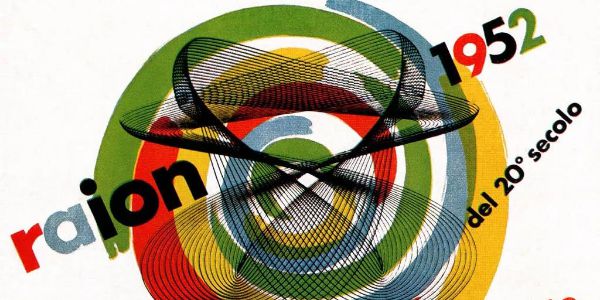
他的设计疯起来真是六亲不认一马克斯・赫伯
Max Huber(马克斯·赫伯)是20世纪欧洲广告界的领军人物,他丰富而多面向的个性,使他的作品也带有灵动且无法预料的迷人风格。
赫伯是最早在意大利的广告海报中尝试使用照相技术的人之一。他将色彩的套印与照片结合使用,制造了强烈的实验意味。然而这种先锋的版面效果却从不会落入杂乱和无序。从上面的作品中,我们能看到赫伯总是能用极度严谨的设计功力将版面控制在一个微妙的平衡点,甚至还带点迷幻。这与他所接受的瑞士设计教育密不可分。他的设计就像他最痴迷的爵士乐一样,灵动随意,极富变化性,却又有着精准的节奏感。下面这些作品运用的都是类似的手法,但却各有各的魔幻。你感受一下。
米兰工业大学室内建筑与设计史教授,意大利知名策展人 Giampiero Bosoni 对赫伯有着极高的评价。
Giampiero Bosoni
“他是多种美妙事物的混合体,他有着非凡的艺术天赋和完美的设计功力,他像个孩子一样活泼和坦率,同时又具备瑞士学派的高度严谨,他热爱创新,拥有永不枯竭的好奇心,随时能够抓住不可预测的新想法,并能以一流的专业水准精确地呈现出来。”
设计师简介
Max Huber(马克斯·赫伯)1919年出生于瑞士,当时第一次世界大战刚过,整个欧洲元气大伤,选择在这个时间点出生在欧洲的他,注定了设计生涯与战争有着密不可分的关系。赫伯从很小的时候起,就表现出了极强的视觉艺术天赋,1935年,17岁的赫伯高中毕业后进入了瑞士苏黎世工艺美术学院,但由于家人无力承担他的学费,赫伯入学不到一年就开始了半工半读的状态。然而没钱根本不算什么,因为接下来你将目睹他一边逃难一边做设计。你再难你也没他难。
赫伯在学校结识了许多优秀的艺术家,其中对他影响最大的是他的图形和摄影老师Alfred Willimann,他让赫伯接触到了俄国构成主义和德国的包豪斯,引导赫伯走向了一种严谨和理性的设计风格,也就是我们今天说的“瑞士风格”,也叫“国际印刷风格”。说到瑞士风格,我们脑中多多少少都会浮现出一些性冷淡的设计,它们强调清晰,可读性和客观性。风格的标志是不对称的布局,使用网格系统,无衬线字体以及左侧对齐右侧参差的文本编排方式。
魏玛时期的包豪斯学院
国际印刷风格是德国包豪斯的探索成果在瑞士的延续,由于包豪斯在德国被纳粹关停,一部分遭到打压的艺术家被迫流亡到了瑞士。他们与许多年轻的瑞士同事一起开创了国际印刷风格,奠定了瑞士平面设计的基础。
然而欢乐的时光总是短暂的,一转眼就到了分手的时刻。1939年二战爆发,虽然作为中立国的瑞士奇迹般地没有被战争波及,但身处战乱年代的瑞士,全国上下随时做好了抵抗的准备。为了躲避征兵,赫伯决定先走一步,1940年12月他来到意大利米兰发展,这使他成为众多进军米兰的瑞士设计师中的第一人。21岁的赫伯初到米兰,就决定到博格瑞工作室(STUDIO BOGGERI)应聘。
STUDIO BOGGERI,意大利最重要的设计工作室之一
问题是他几乎说不了几句意大利语,即便如此,在创始人Antonio Boggeri看到了赫伯留下的名片之后,立即决定雇用这位年轻的设计师。因为Boggeri注意到名片上整齐的小写字,看起来是印刷的,但其实是手写的。字母的间距微小却精确,足见赫伯当时扎实的设计功底。
Max Huber手写名片,1951
我没有找到当时他应聘用的那张名片,但这张手写名片是赫伯加入博格瑞后于1951年制作的,尺寸是60mm*135mm,上面的手写文字大小相当于Bodoni的10pt。这就是别人的手。
赫伯把米兰,尤其是博格瑞工作室,看作是一个插图、绘画、摄影和印刷都可以融合在一起熔炉。在博格瑞,他又能与设计界的领军人物、知识分子和前卫艺术家们在一起愉快地玩耍了。
赫伯在博格瑞从事的工作包括设计海报、画册、展会、橱窗、文件夹、文具、广告、商标——事实上,他所开展的工作,其他国家直至20多年后才出现。
不过赫伯初到米兰的设计工作仅维持了18个月就被迫终止了,1942年由于战争原因,赫伯再次决定跑路,返回瑞士躲避战乱,一年之后,英军登陆西西里岛,战火烧至意大利本土。
年轻的赫伯与他的设计师朋友们
回到瑞士后赫伯也没闲着,他在苏黎世加入了瑞士艺术家联盟协会,该协会的领导人也叫马克斯——马克斯·比尔(Max Bill)。这位马克斯早在1936年的米兰三年展中,就通过其展馆设计得到了设计界的肯定。在战争期间,赫伯与比尔合作从事展览设计工作,受到其很大的影响。
MAX BILL(建筑师,工业设计师,平面设计师,画家)
1970年
1946年,二战结束后的第一时间,赫伯又搬回了米兰,他认为在战后,设计有恢复人类价值的能力。这种人性化的设计理念在20世纪50年代在整个欧洲流行起来。当时他被意大利最大的出版商Einaudi任命为创意总监。
La formazione della Cina Moderna
书封,Einaudi
作为该出版物的创意总监,他接触了大量战后的意大利知识分子。随后的岁月被认为是他一生中最富有成效的时期。他在20世纪40年代后期制作了一系列史诗级且富有影响力的设计。作为一名热衷爵士乐的粉丝,他设计了许多令人惊叹的唱片封面,音乐杂志和爵士音乐节,都是20世纪平面设计史上非常经典的设计案例。
Max Huber 与“爵士乐之父”Louis Armstrong
上图是赫伯与自己的偶像路易斯·阿姆斯特朗握手的画面,见到爱豆的赫伯秒变迷弟。Giampiero Bosoni 曾在瑞士策划过一场专门以爵士乐为主题的赫伯作品展,展出的大量作品中还包括许多从未出版过的作品,足见赫伯对于爵士乐的狂热。
赫伯对平面设计的贡献得到了高度赞赏,最终他于1954年获得了著名的Compasso d'oro奖(意大利工业设计界的最高荣誉,同时也是欧洲同类设计奖中的首个奖项)。此外,他于1958年作为演讲者参加了第一届印刷术国际研讨会(纽约艺术指导俱乐部)。
随着他的艺术作品在国际上受到欢迎,越来越多的国家展出了他的作品。1965年,日本设计委员会在东京松屋艺廊举办了一场展览,展示了赫伯的作品。这次展览使他与日本建立了密切的联系,他还在这里找到了日后的妻子,日本设计师河野鹰思的女儿,插画家Aoi Kono。从此全家都是搞艺术的。
Max Huber 与 Aoi Kono
晚年,赫伯开始教授设计,他的一生都在从事设计工作。直到1992年,作为一位影响了世界平面设计史的设计师,Max Huber在瑞士门德里西奥逝世,享年73岁。
m.a.x. Museo
2005年,m.a.x. Museo——一个致力于纪念 Max Huber 的博物馆——在瑞士 Chiasso 成立,用于保存他的个人档案及作品,也用于展出许多优秀的当代平面艺术家的作品,同时也是平面设计爱好者的朝圣之地。
作品解析
fotolux 销售目录〈1940〉
Fotolux是一家照片复印公司,画面中的主体Fotolux采用了镜像的手法,用将“复制”这一概念视觉化的方式来表现公司的核心业务。这是赫伯初到米兰,在Boggeri工作室的早期设计之一。其中精细的手写字体,考究的小写字母间距,透视和有限颜色的使用,都展示出赫伯在瑞士接受设计教育的特点。
葛兰素实验室的 Adexolin(阿霉素)
药学手册〈1941〉
Adexolin是一种维生素A、D制品,这本药学小册子介绍了维生素A和D的“生物学前提和治疗应用”。完全听不懂。在当时的历史背景下,米兰的许多设计师的设计作品都依赖于药品宣传。赫伯将产品名中的“AD”与维生素“A”和“D”单独涂成白色,以强调产品本身和所含维生素之间的联系。
Teweka 金属扣环广告〈1941〉
这幅广告设计采用了照相技术,照片显示金属扣环就像是刚刚从盒子里掉出来散落一地的样子,是很有现场感的一张照片。赫伯将这张照片铺满整个版面,但是版面还得有个主体,他从背景中挖出一个扣环的放大轮廓,将品牌名称和唯一的一句广告语与扣环轮廓组成一个组合,颇具视觉冲击。
Procedimento CIM 传单〈1942〉
这是二战期间的一张传单,下面的绿色文字写的是“利用互补色的原理,为窗户涂上不同的颜色,可以使入射的光线完全变暗。” 赫伯用一张图片就完美解释了光线变暗的技术原理,图中的手拿着两块互为补色的透明醋酸纤维板,上面的箭头代表入射光线,而下面的虚线从纤维板交叠处穿出,代表光线先后透过两层纤维板后已经被吸收。旁边的小字写着:“适用于工厂、工业建筑、军事设施和仓库。”这一案例展示了将原理视觉化的过程,整个版面简洁,透彻,产品的技术与卖点一目了然。鼓掌。
Sirenella 爵士乐舞厅海报〈1946〉
这是二战结束,赫伯返回米兰后最高产的一个时期的作品。当时的大环境是“国际印刷风格”盛行,还记得前文的“国际印刷风格”么,本文中为数不多的硬核知识点。虽然当时市面上流行的是秩序和理性,但我在他为 Sirenella 设计的海报中看到的确是疯狂,跳跃和节奏感。海报采用了赫伯最擅长的照片与色彩叠印,版面编排纵横交错,加上非常强烈的纯色,制造出了前所未有的丰富和强烈的视觉特征。彩色圆圈强烈地暗示了敲击产生的声音。在这张海报里,我感受不到理性,我只想让他冷静。
为什么会有如此颠覆性的设计?其中一个原因是源于赫伯对爵士乐的狂热,或许是因为爵士乐的多变和灵动与赫伯永不枯竭的好奇心和活泼的内心不谋而合。这家舞厅的开业赫伯为它设计了许多东西,包括壁画。另一个原因是20世纪30年代至50年代前后,仅有少数设计师在探索这种与国际主义颇为不同的风格,但赫伯正好就是其中重要的代表人物。他的实验性设计对意大利设计的发展产生了深远的影响。
无线电杂志封面〈1948〉
这是为意大利广播电视公司制作的杂志封面,这张封面设计足够形象,以至于不用太多解释。用报纸做成的环形剪报不断重复形成“声波”,通过中间的麦克风传播出去就是广播。标题和少量的文字部分利用两个色块的形式倾斜排列,强调了动态性。整张海报没有任何不必要的形式感和复杂冗余的效果,反而让正确设计的思路变得清晰可见。一个面向大众的好的设计应该是让你在感叹创意精彩的同时,也觉得恰如其分合情合理,而不是一阵酷炫之后的一头雾水。
La Rinascente 连锁百货公司〈1950〉
La Rinascente 连锁百货公司注册于1917年,二战期间其多家商场遭受到毁灭性打击,而且据说新商场好不容易筹备完毕,正要开业就突遇大火。可能是战乱搭配了水逆。直到1950年,位于大教堂广场的 Rinascente 商店再次以精美的风格开业才重塑辉煌。这一年赫伯为其设计了全新的标志。
Huber 在将设计好的标志手工放大
赫伯把粗体Futura的字母“R”与bodoni的小写字母“i”这两个高对比性的元素结合在一起,这种结合象征着米兰作为北方与地中海文化交汇的聚集地的地位。这种把对立元素结合在一起的做法直到今天一直还是广告领域常用的手段。
La Rinascente 海报,1951
当然赫伯做的不止于设计标志,而是整个品牌形象的重塑。在1950年到1954年间,他帮助La Rinsacente百货公司建立了统一的风格系统。他把店内标签、包装和宣传资料与橱窗、海报和媒体广告很好地联系起来,组织在统一的视觉系统之中。是不是听起来很熟悉?其实就是我们今天所说的“VI”(视觉系统),只不过VI的概念是在几十年后提出的。
La Rinascente 包装纸
接下来我会介绍几个La Rinascente的产品目录,这样更容易感受这种设计上的连续性。
La Rinascente 钓具产品目录〈1951〉
这个案例生动地展示了什么叫生动的设计。赫伯用浅蓝色的背景来暗示水的存在,并将黑色的真实鱼的图案与白色的简化鱼的轮廓搭配在一起,从而制造出光影和景深的效果。还记得很久之前的一篇讲颜色的前进和后退的文章么?这种手法直到今天依然是丰富画面层次的基本方法之一。你用过么?被鱼群包围的主标题我们都知道具有引导视线的作用,但除此之外,它还有一层含义就是像一个饵一样,令所有的鱼都趋之若鹜。为什么这么说呢?当你展开整个画册,就能发现其中的玄机。
一只渔网早就等在画册的封底,左上角的手暗示了人的存在,而我已经在期待这场收获,甚至还有点小紧张。我想一个完美的设计就应该是这样,既在意料之外,又在情理之中。
La Rinascente 运动产品目录〈1951〉
这本目录封面是意大利平面设计史上最伟大的杰作之一。它仅使用了两种颜色的双色印刷,就让一个原本静止的画面动了起来。我们可以通过绿色草地上空旋转的白色球杆轨迹,清楚地看到整个挥杆过程。所谓大力出奇迹,这一杆的力道与优美程度我给满分,想要知道球进没进,还是要翻到背面。
页面左下角用了一张球的单色照片和一个椭圆形表现出了球向洞中掉落的效果。在那个技术受到很大限制的时代,单纯凭借“设计力”用最简单的元素挑战多变的画面效果,使这些作品在今天看来依然具有很强的视觉冲击。并且整个版面无论是单独看正面或背面还是展开来看整体,画面中的元素摆放都能做到灵活多变的同时又相互呼应保持平衡。
La Rinascente 夏季时尚服饰目录〈1984〉
这是一本1955年的时尚画册,当时的米兰时尚已经走在了很前面。赫伯采用了一组模特穿着泳装的背影来展现主题“夏日时尚推荐”。不得不说赫伯的时尚触觉非常敏锐,一下就抓住了“时尚圈”永恒不变的审美取向“平胸加美背”。我不知道他具体为什么选择了一组背面照,但就时尚这个主题来讲,这个效果在今天看来也还是很时尚。赫伯用三条多彩的色块作为模特的座位,与清爽的白色背景搭配出夏日的感觉,你能够想象这就是她们坐在泳池边的场景。
Coin 百货标志〈1955〉
这是意大利一家大型百货连锁店,由Vittorio Coin于1926年在威尼斯的皮亚尼加建立。商场的名称就取自创始人的名字。可能是为了强化“coin”(钱币)在人们脑中的印象,赫伯在字体设计中巧妙地强调了字母的“圆度”,也就是我们今天说的“几何型”无衬线字体。同时他将字母“i”的点放大成一个圆,更加强调的了“圆”的印象,也让这个大圆点的重量与字母的其他部分形成了有效的对比,形成了这个标志的记忆点,相信你看过一次就不会忘记。而且这样的设计也大大增加了它作为一个招牌的识别度。因为这个“i”就像一个灯牌一样在向你招手,商场在这边儿~上来玩儿啊~看一下下面的应用场景你应该会认同我的说法。
那个大圆点是不是格外显眼,仔细看会发现这张照片中还有一个竖向排列的“coin”灯箱,它的效果与赫伯制作的标志灯箱形成了鲜明对比,在识别度和记忆点上高下立判。
Monza 赛道海报〈1957〉
Monza一级方程式赛道于1922年正式开放使用,是世界上第三个专业级赛车赛道。赫伯为Monza赛道制作的第一张海报发布于1948年。
你可以看到这张海报上面既没有赛道也没有车,因为赫伯利用弯曲的彩色条纹直接将赛场上的“速度”给可视化了。这个小思路高不高级你就说。
看看人家这透视这辅助线,他利用严谨透视在一个纯抽象的画面里营造了空间纵深和运动感,是整个版面异常丰富。大面积的平涂色块和手绘字母的反复叠加使这个设计看上去像一幅抽象画。后来切割图形和平板颜色成为了意大利平面设计的常规元素,而赫伯创造性的设计是其中毋庸置疑的先锋。
在这张1955年的海报中,摄影照片的巨大倾斜角度与文字的方向一致,共同营造了比赛中的超高速度,我们可以看到照片中赛道所形成的弧线与上一张海报中线条的效果如出一辙。到了1957年,赫伯将这两张海报中使用的方法进行融合,完成了下面这张海报,也是他最著名的设计作品之一。
赫伯将表现速度的彩色条纹与大角度的赛车照片叠加,使两种完全不同的设计元素之间产生强烈的戏剧性,同时又保持了严谨的形式和平衡的构图,达到了繁中有序的目的。在20世纪的平面设计史中,不同的书籍对于max huber的表述会有所不同,有的人认为他是瑞士风格的代表,也有的人会把他放在意大利米兰风格的部分来介绍,而这幅为Monza赛道制作的海报是将这两种风格完美融合的典型例子。
Esselunga 超市标志〈1957〉
这是意大利第一家连锁超市的标志,你发现了么,这个标志中没有超市的名称。因为这家超市最初没有名字,就叫“超级市场”。
赫伯设计的这个标志中最核心的部分就是一个长长的“s”。你看这个“s”它又大又长,充分体现了这个market有多super。由于这个“s”具备很强的记忆点且非常易于传播,久而久之人们提到这家超市时都会以“长s”作为它的简称,以至于最终这家超市真的将自己命名为Esselunga(long s),买个标志赠送个名字。
1960年,超市开始启用新标志,赫伯将超市名称Esselunga与标志性的“s”组合,更新的同时,曾经那个最具识别性的“s”形象没有改变。
20世纪70年代初期,标志再次经历了一轮更新,最初的“s”依旧得到延续。
西西里岛质量标志〈1960〉
这是一个应用在西西里地区的质量标志,有点类似于我们国家之前使用过的蓝色“QS”标志。将采用无衬线字体的地区名称放在一个类似Garamond的大写“Q”(quality)中。Q拖着一条非常长的尾巴,与中间的无衬线字体搭配出一种既优雅又现代的气质,让我联想到英国时装品牌Alexander McQueen。赫伯这样设计的用意是想要将Q与区域名称绑定在一起,建立一个符号系统,使其他地区可以通过改变中间的区域名称来制作统一的质量标志。
Nicola Moneta 挂历〈1964〉
Nicola Moneta是一家意大利印刷出版公司,与赫伯有着多年的合作。这张挂历乍看之下,除了依旧严谨的版式之外,最特别的点就是其中中文字的加入,其实严格来讲这是“日文”。这一设计的加入是赫伯的妻子兼合作伙伴Aoi Kono的贡献。
其实这张挂历真正的设计意图在于颜色,它使用了到目前为止最为丰富的色彩。我统计了前文中所有放出的作品,它们可能给你留下了丰富饱满的色彩印象,但任意一幅作品用到的颜色数量都不超过4种,而这张挂历却使用了超过15种颜色。
其实这个挂历是一个实验性设计,它尝试了当时最新的色彩和印刷技术。平面设计的历史如果我们单从技术的角度来看,就是印刷技术的进化史,平面设计与印刷的发展可以说是紧密结合相互促进的。那时的设计师除了在已有的技术之内发掘更多的表现形式之外,还要不断探索新技术的可能性。
今天我们身处一个技术爆炸的时代,新技术层出不穷,已经超过我们自身更新的速度。大家越来越注重形式,年年跟潮流,反而没什么人在意设计思路。其实从根本上,设计的核心从服务少数贵族阶级转到服务大众之后,已经从单纯的追求美转化为功能优先。直到现在我们做设计之前要弄清楚的依然是,替谁传达,向谁传达和怎么传达。脱离了功能性的形式感不能算是设计,所以设计思路永远是重中之重。
如果你有留心就会发现,这次的所有案例,都只用到了平面的字体、平面的色块和黑白照片这三种元素,但放到现在来看,依然足够精彩,通过今天的案例,我们应该能意识到不拼“效果”,也能做设计。